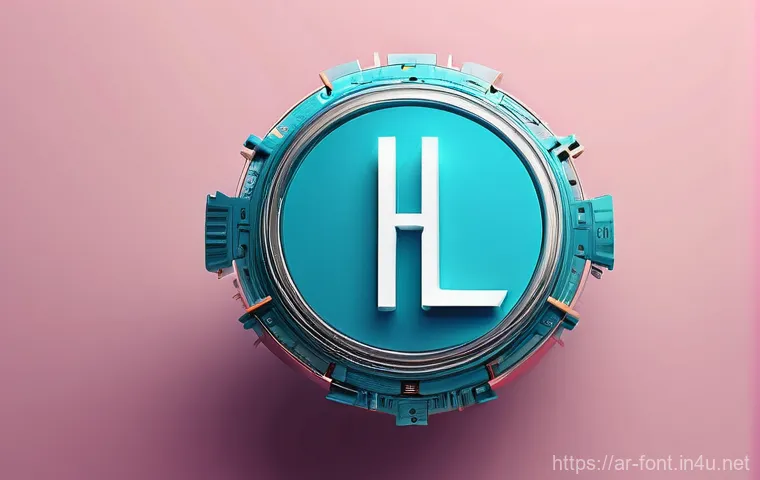
سر الخط الأمثل: اجعل علامتك التجارية تتألق!
أهلاً بكم يا رفاق! كيف حالكم اليوم؟ أتمنى أن تكونوا جميعًا بأفضل حال وأنتم تستعدون لخوض غمار عالم الإبداع والتميز. تعلمون، في عالمنا الرقمي سريع التطور، لم يعد مجرد وجود شعار أو شعار جذاب كافيًا للتميز.
فالهوية البصرية لعلامتكم التجارية هي مفتاح النجاح، واختيار الخط المناسب لها ليس مجرد تفصيل جمالي، بل هو استراتيجية كاملة تؤثر بعمق على كيفية تواصلكم مع جمهوركم وتترك انطباعًا يدوم طويلاً في أذهانهم.
فالخطوط، يا أصدقائي، ليست مجرد حروف مرصوفة، بل هي لغة صامتة تحمل في طياتها شخصية علامتكم التجارية وقيمها، وتعكس روحها للعالم. وقد لاحظت من خلال تجربتي الطويلة في هذا المجال، وكما تؤكد أحدث الدراسات في التسويق الرقمي لعام 2025، أن الخطوط تلعب دورًا حاسمًا في بناء الثقة والمصداقية، وجذب الانتباه، وحتى في التأثير على قرارات الشراء.
فهل فكرتم يومًا كيف يمكن لخط واحد أن يغير نظرة العميل بالكامل؟ أو كيف أن مواكبة أحدث اتجاهات الخطوط العصرية، بما في ذلك الخطوط العربية الإبداعية، يمكن أن تضعكم في مقدمة المنافسة وتزيد من تفاعل جمهوركم؟دعونا نستكشف سويًا في السطور التالية كيف يمكننا اختيار الخطوط التي تُلهم وتجذب، وكيف نُبقي علامتنا التجارية حيوية ومواكبة للمستقبل!
يا أهلاً وسهلاً بجميع عشاق الجمال والإبداع في عالمنا الرقمي! كيف حالكم أيها الأصدقاء؟ أتمنى أن تكونوا دائمًا في قمة نشاطكم وحماسكم. كما ذكرت لكم في المقدمة، اختيار الخط المناسب لعلامتكم التجارية مو مجرد قرار بسيط، بل هو رحلة كاملة تلامس فيها روح علامتك وتجسدها بصريًا للعالم.
واليوم، بفضل بحثي المتعمق وتجاربي الشخصية اللي اكتسبتها مع سنوات في هالمجال، ومع الاطلاع على أحدث ما توصلت إليه دراسات التسويق الرقمي لعام 2025، صرت متأكدة أكثر من أي وقت مضى إن الخط هو لغة صامتة لكنها تحمل في طياتها الكثير من القوة والتأثير.
ترى، هل فكرت يومًا أن الخط اللي تختاره ممكن يغير نظرة العميل تمامًا لعلامتك التجارية؟ أو كيف أن مواكبة أحدث اتجاهات الخطوط العصرية، خصوصًا الخطوط العربية اللي تعبر عن أصالتنا، يمكن يخليك في المقدمة ويزيد من تفاعل جمهورك؟ اليوم راح نمشي خطوة بخطوة ونكتشف سويًا كيف نختار الخطوط اللي مو بس تلفت النظر، بل تُلهم وتجذب وتخلي علامتنا التجارية حيوية ومواكبة للمستقبل.
الخطوط: نبض هويتك البصرية وروح علامتك التجارية
يا جماعة الخير، الخطوط في عالم التصميم أشبه بالصوت البشري تمامًا، كل خط له نبرة خاصة وشخصية مميزة. لما تختار خط معين، أنت ما قاعد تختار مجرد شكل حروف، بل تختار “صوت” لعلامتك التجارية. هذا الصوت هو اللي راح يوصل رسالتك ويحكي قصة براندك من غير ما تنطق ولا كلمة. من خلال خبرتي الطويلة في مجال التصميم ومساعدة الكثير من العلامات التجارية، لاحظت أن الخط يلعب دورًا حاسمًا في بناء الثقة والمصداقية. تخيل معي، لو عندك شركة استشارات مالية، هل راح تختار خط مرح ومزركش؟ طبعًا لأ! لأن هذا الخط ما راح يوحي بالجدية والاحترافية المطلوبة. بينما لو كان عندك مقهى شبابي، أكيد راح تختار خط عصري ومريح للعين يعكس أجواء المكان المبهجة. يعني الخط مو بس جزء جمالي، هو استراتيجية كاملة تتجسد في كل حرف، ويأثر بعمق على كيفية تواصلك مع جمهورك، ويترك انطباعًا يدوم طويلًا في أذهانهم. فعلاً، الخطوط هي اللغة الصامتة اللي تحمل شخصية علامتك التجارية وقيمها، وتعكس روحها للعالم.
التأثير النفسي للخطوط على جمهورك
صدق أو لا تصدق، للخطوط تأثير نفسي رهيب على المتلقي. كل خط يحمل في طياته شحنة عاطفية معينة. فمثلاً، الخطوط الكلاسيكية زي “سيريڤ” غالبًا ما توحي بالفخامة، العراقة، والموثوقية، وتلاقيها في المجلات الفاخرة أو العلامات التجارية التقليدية. أما خطوط “سانس سيريڤ” (بدون زوائد)، فتعطي شعورًا بالحداثة، البساطة، والكفاءة، وغالبًا ما تستخدمها شركات التكنولوجيا والشركات الناشئة. أنا شخصيًا، أؤمن بأن فهم هذا التأثير النفسي هو مفتاح تصميم الهوية البصرية الناجحة. لو كنت تستهدف جمهورًا يبحث عن الابتكار والتطور، طبيعي تختار خط عصري وخفيف. ولو كنت تستهدف جمهورًا يقدر الأصالة والتاريخ، فالخطوط التقليدية راح تكون خيارك الأول. الأمر كله يرجع لفهم عميق لجمهورك وما يلامس مشاعرهم، وهذا ما يميز المحتوى الأصيل الذي يلمس الوجدان.
كيف تختار الخط الذي يروي حكاية علامتك التجارية؟
اختيار الخط المناسب لعلامتك التجارية أشبه باختيار الملابس المناسبة معينة. لازم يكون فيه تناغم وتوافق تام بين شخصية علامتك التجارية والخط اللي بيمثلها. أول خطوة لازم تسويها هي تحديد شخصية براندك بوضوح. هل هو براند مرح وعفوي؟ ولا جاد ورسمي؟ ولا فخم وعصري؟ بعد ما تحدد هالشي، وقتها تقدر تبدأ رحلة البحث عن الخط اللي يعبر عن هالجو. من تجربتي، أشوف كثير مصممين يختارون الخط بناءً على جماليته فقط، وينسون الجانب الوظيفي وسهولة القراءة، وهذي بحد ذاتها مشكلة كبيرة. تخيل إنك عامل إعلان لمنتجك وخط الإعلان غير واضح أو متداخل، كم زبون ممكن تخسره بسبب هالشي؟ كثير جدًا للأسف! لذلك، التوازن بين الجمالية والوظيفة هو الأساس. لازم الخط يكون جذاب ومواكب للموضة، لكن الأهم إنه يكون سهل القراءة على جميع الأجهزة والشاشات، سواء كان على الجوال، الكمبيوتر، أو حتى في المطبوعات. دايمًا أقول للمصممين الشباب: حطوا نفسكم مكان العميل، هل راح يقرأ هالخط بسهولة؟ وهل بيوصل له الإحساس اللي تبغونه؟
فن الخطوط العربية: أصالة متجددة تجمع بين العراقة والحداثة
يا أصدقائي، الخط العربي هذا عالم بحد ذاته! ما في لغة تتمتع بهالتنوع والجمال في الخطوط زي اللغة العربية. من الخط الكوفي العريق اللي يأسرك ببساطته وقوته، للخط النسخ اللي يتميز بوضوحه وجماله، للديواني والفارسي اللي فيهم فن وذوق ما بعده ذوق. صراحة، أنا كمدونة عربية، أعتبر الخط العربي كنزًا لازم نستغله ونبرزه في تصاميمنا. اختيار الخط العربي المناسب لعلامتك التجارية مو بس يعكس هويتك، بل يلامس جزءًا عميقًا في وجدان جمهورك العربي. فيه فرص إبداعية هائلة في دمج أصالة الخط العربي مع اللمسات العصرية. لاحظت إن فيه تحديات في تصميم الخطوط العربية عشان تتناسب مع التكنولوجيا الحديثة وشاشات العرض، لكن في المقابل، فيه مصممين عرب مبدعين قدروا يتجاوزون هالشي ويقدمون خطوط عربية عصرية تحافظ على روح الأصالة وفي نفس الوقت تكون مقروءة وجذابة رقميًا. لما تختار خط عربي، لازم تفكر في كيفية ظهوره على مختلف الشاشات ومدى سهولة قراءته، خاصة مع التشكيل والحروف المتصلة. شخصيًا، كل مرة أشوف تصميم يستخدم خط عربي بذكاء، أحس بفخر كبير!
أحدث اتجاهات الخطوط لعام 2025: دليلك للبقاء في الصدارة
لو كنت تبغى علامتك التجارية تكون دائمًا في الطليعة وتلفت الأنظار، لازم تكون على اطلاع بأحدث اتجاهات الخطوط لعام 2025. أنا متابعة هالموضوع عن كثب، وملاحظة إن فيه توجه كبير للخطوط البسيطة والواضحة (Minimalist Sans-Serif) اللي تعطي شعور بالنظافة والحداثة. كمان فيه رجوع قوي لخطوط “سيريڤ” لكن بلمسات عصرية تخليها أنيقة ومناسبة للبراندات الفاخرة. غير كذا، الخطوط المتغيرة (Variable Fonts) قاعدة تكتسب شعبية كبيرة لأنها توفر مرونة هائلة للمصممين، وتقدر تتحكم فيها بأوزانها وأحجامها بكل سهولة. هذه الاتجاهات كلها تهدف لتحسين تجربة المستخدم على مختلف المنصات، وعلشان تخلي المحتوى حقك جذاب ومريح للعين. نصيحتي لك، لا تتبع الترند بشكل أعمى، اختر اللي يتناسب مع شخصية براندك ورسالتك. الأهم إنك تستخدم هذه الاتجاهات بذكاء عشان تضيف قيمة لعلامتك التجارية وتبرزها بشكل مميز.
يا رفاق، لا تختاروا الخط لمجرد أنه “موضة” أو “ترند” لحظي، بل لأنه يعبر عنكم بشكل فريد. خط آخر فادح هو اختيار خط معقد أو زخرفي يصعب قراءته، خاصة في النصوص الطويلة أو على الشاشات الصغيرة.
تذكروا، الخط ليس مجرد زينة، بل هو وسيلة للتواصل الواضح والفعال. وأخيراً، عدم مراعاة تناسق الخط مع باقي عناصر الهوية البصرية، مثل الألوان والشعار، يمكن أن يخلق فوضى بصرية تضر بجمال علامتك التجارية وموثوقيتها.
لقد رأيت عملاء يختارون خطوطاً لا تتناسب مع قيم شركاتهم الجوهرية، وهذا يؤدي إلى رسالة متناقضة تشتت العملاء. اختاروا بحكمة، ودعوا الخط يتحدث عنكم بأفضل صورة ممكنة!